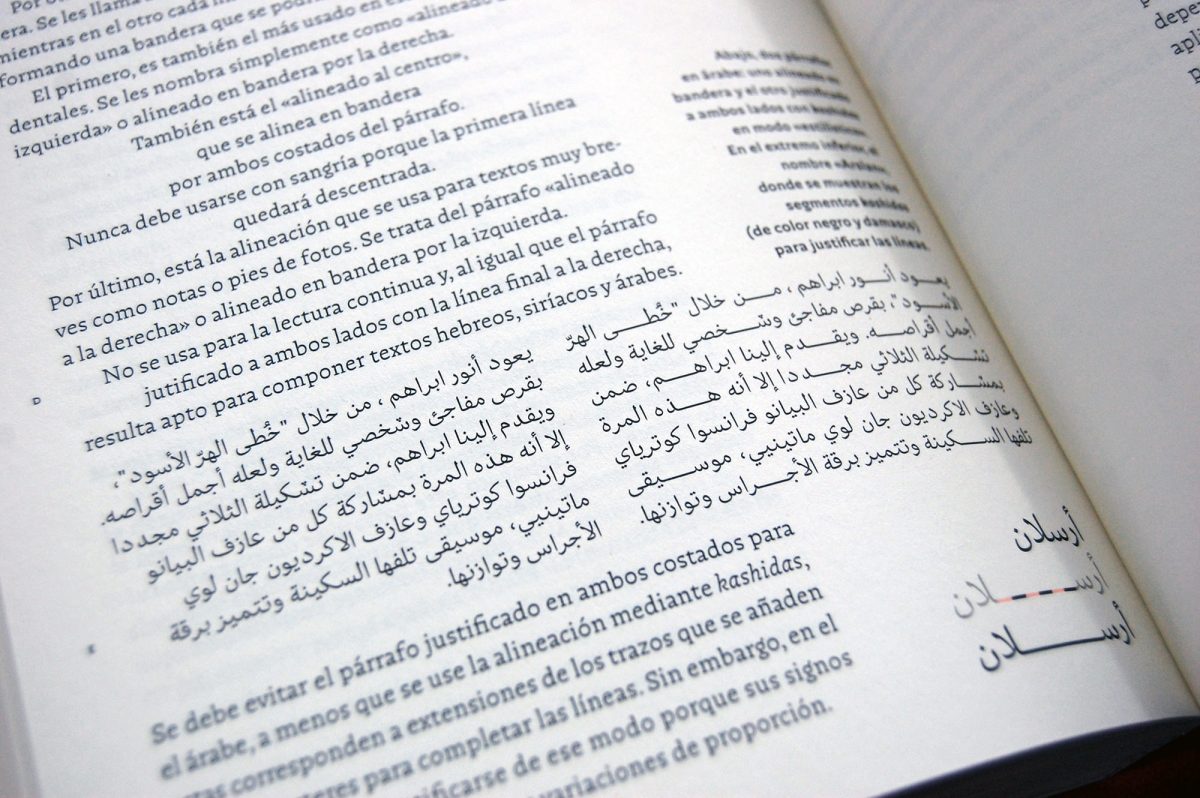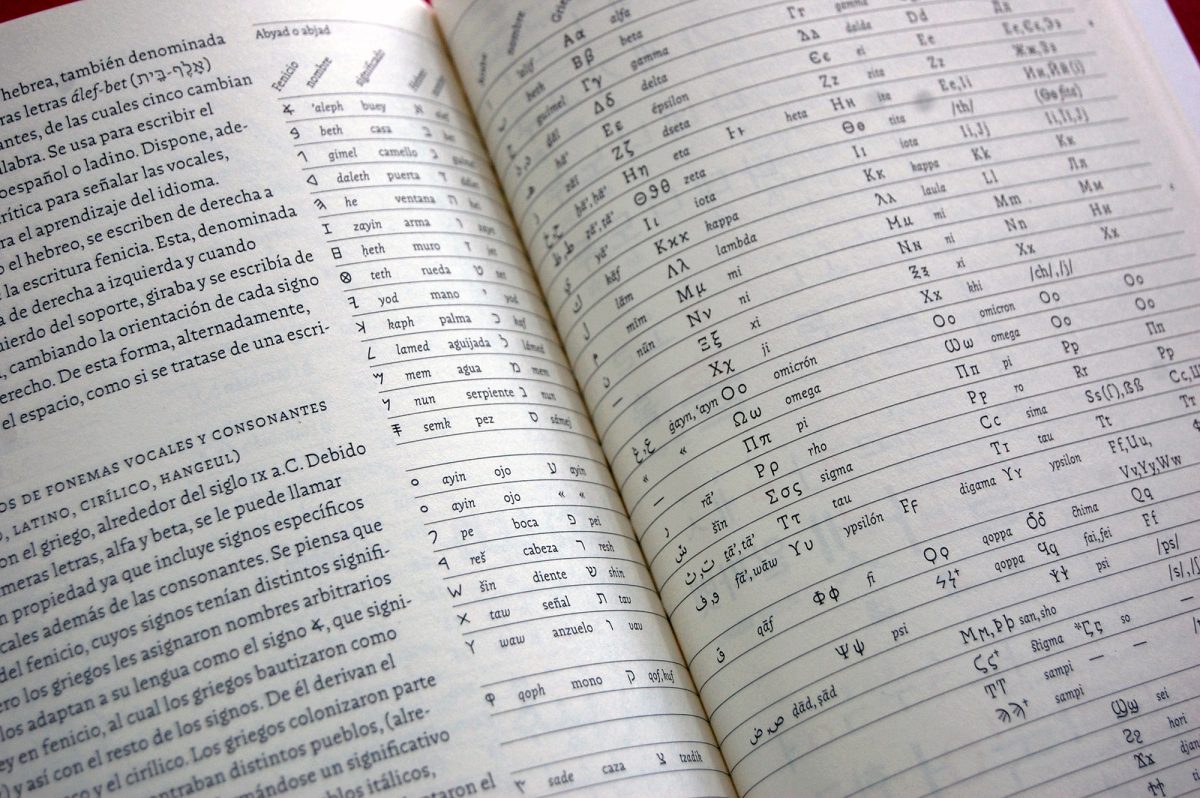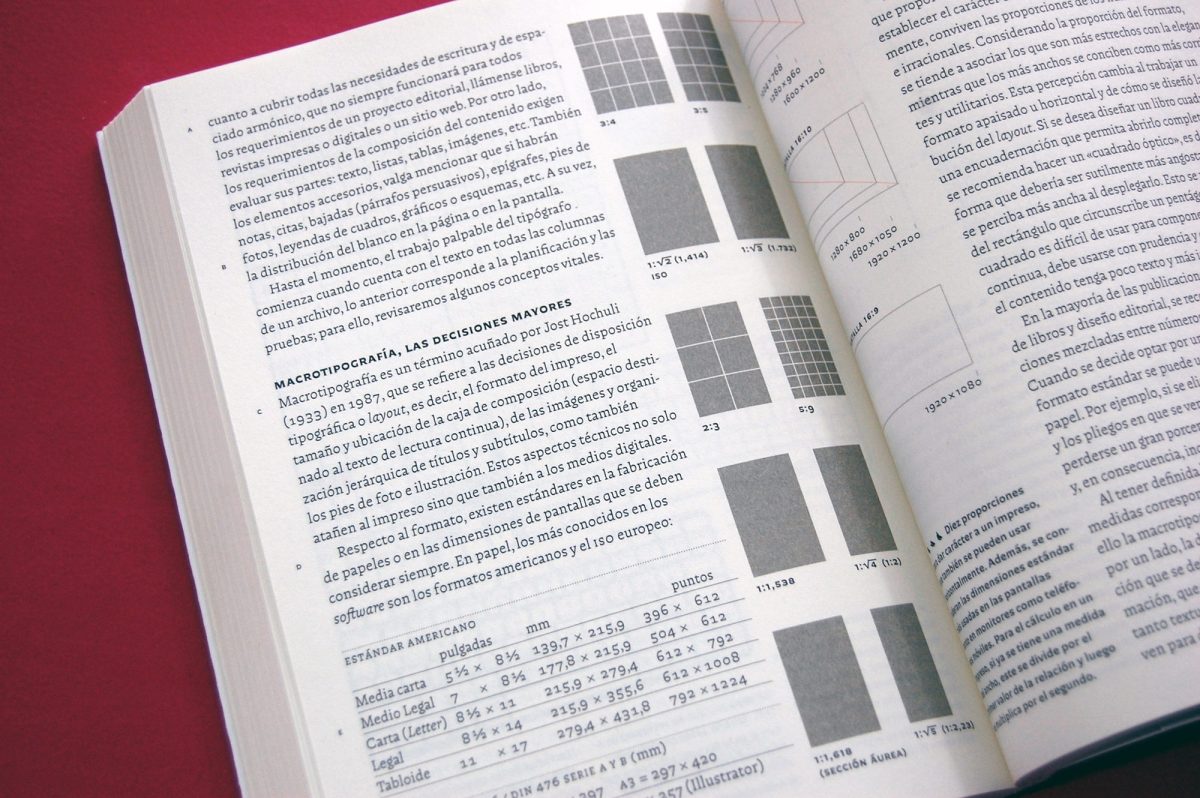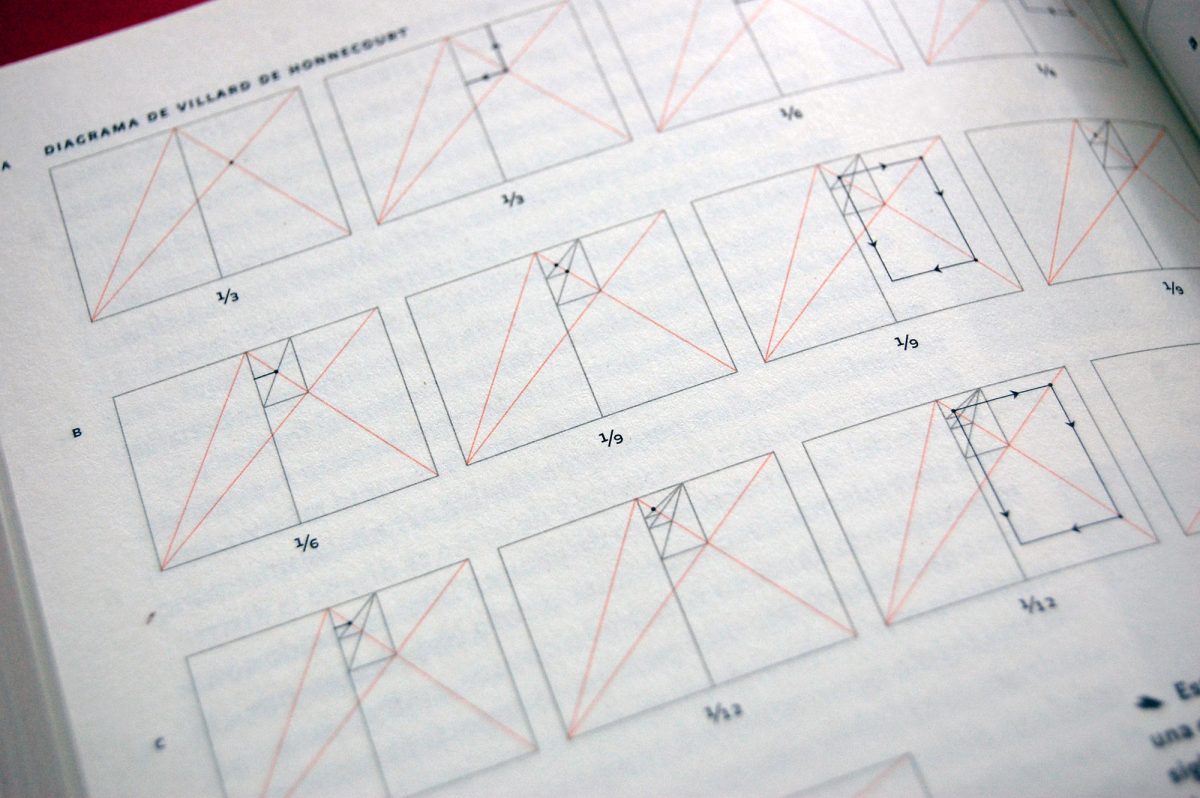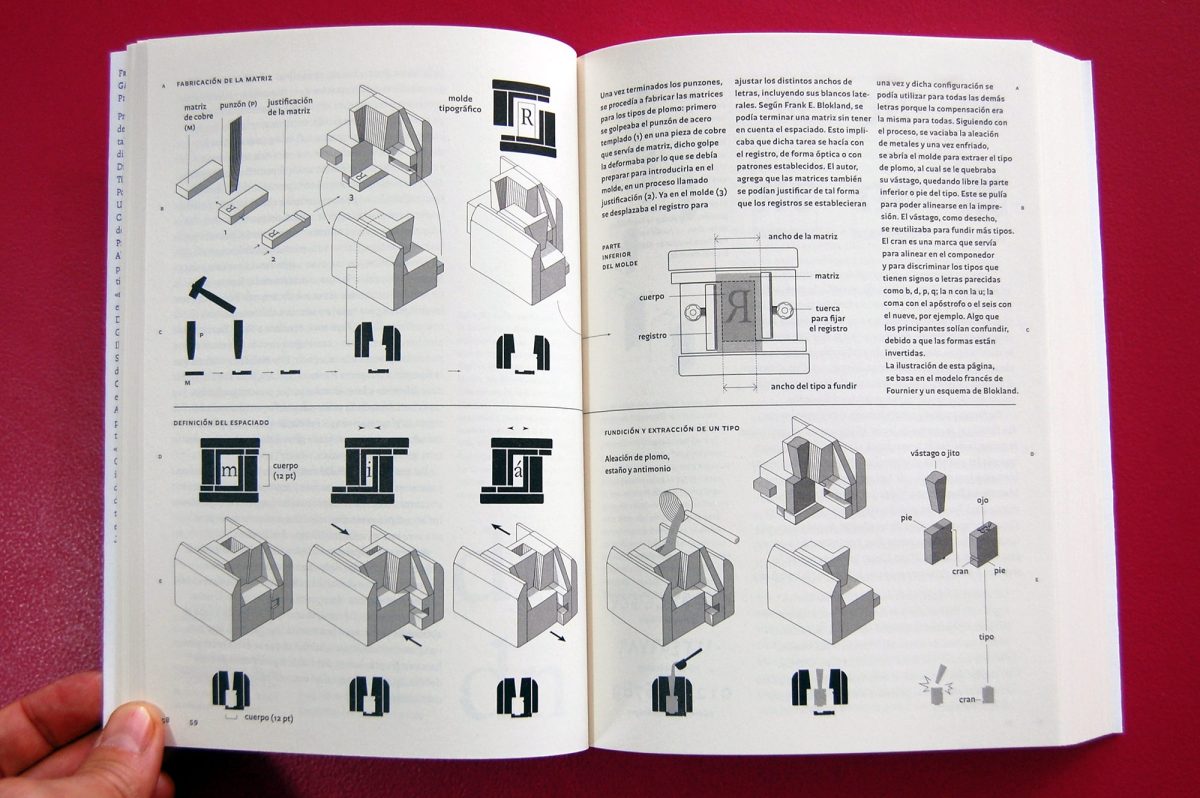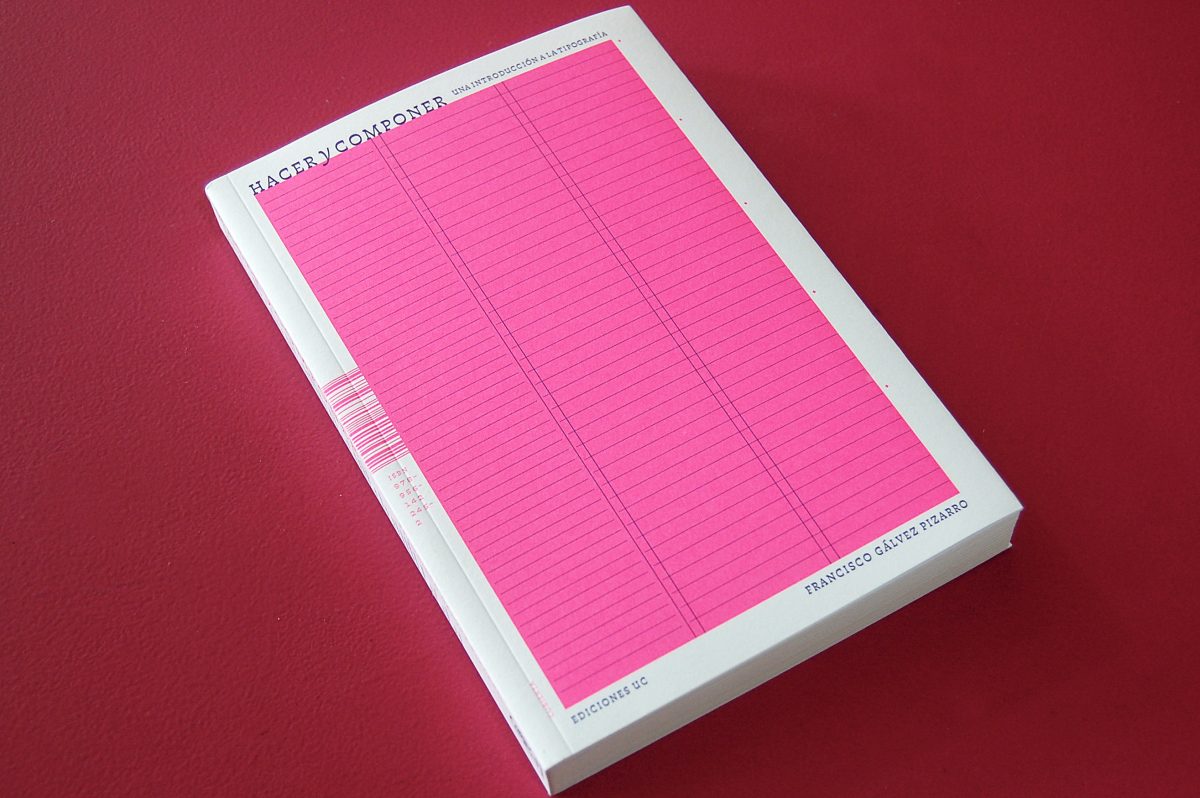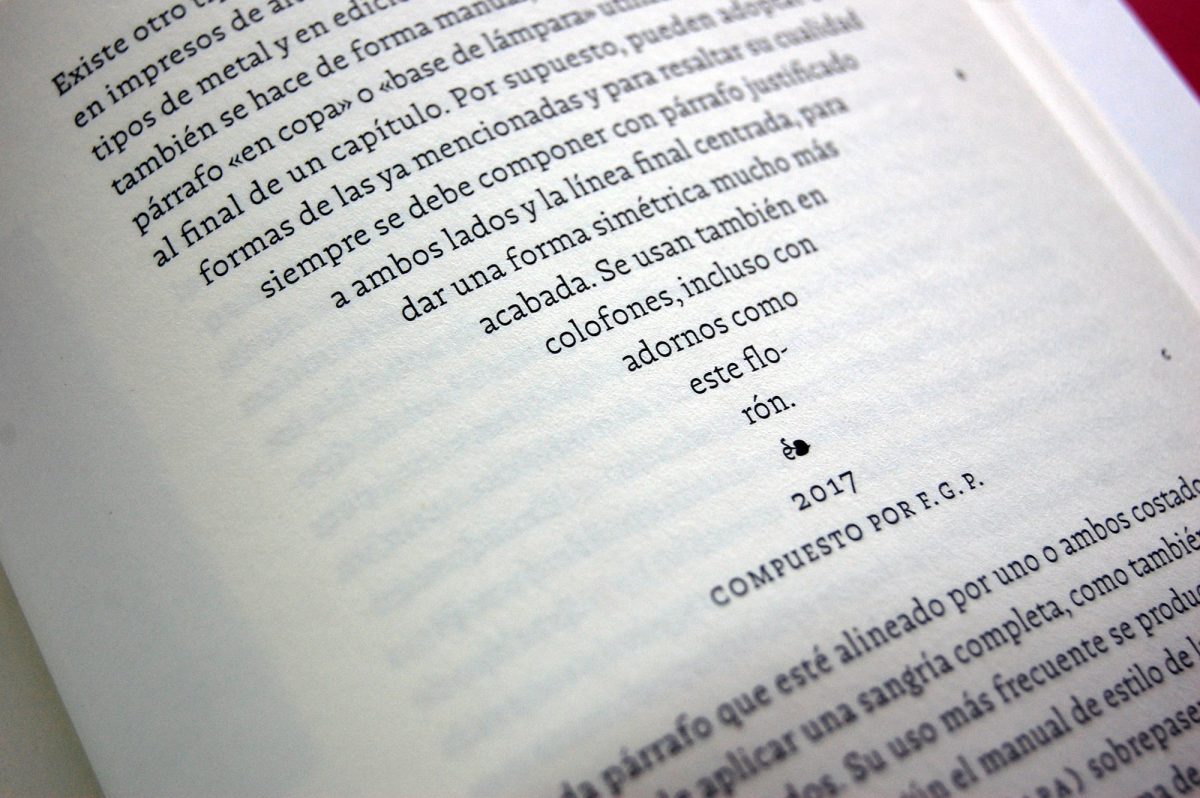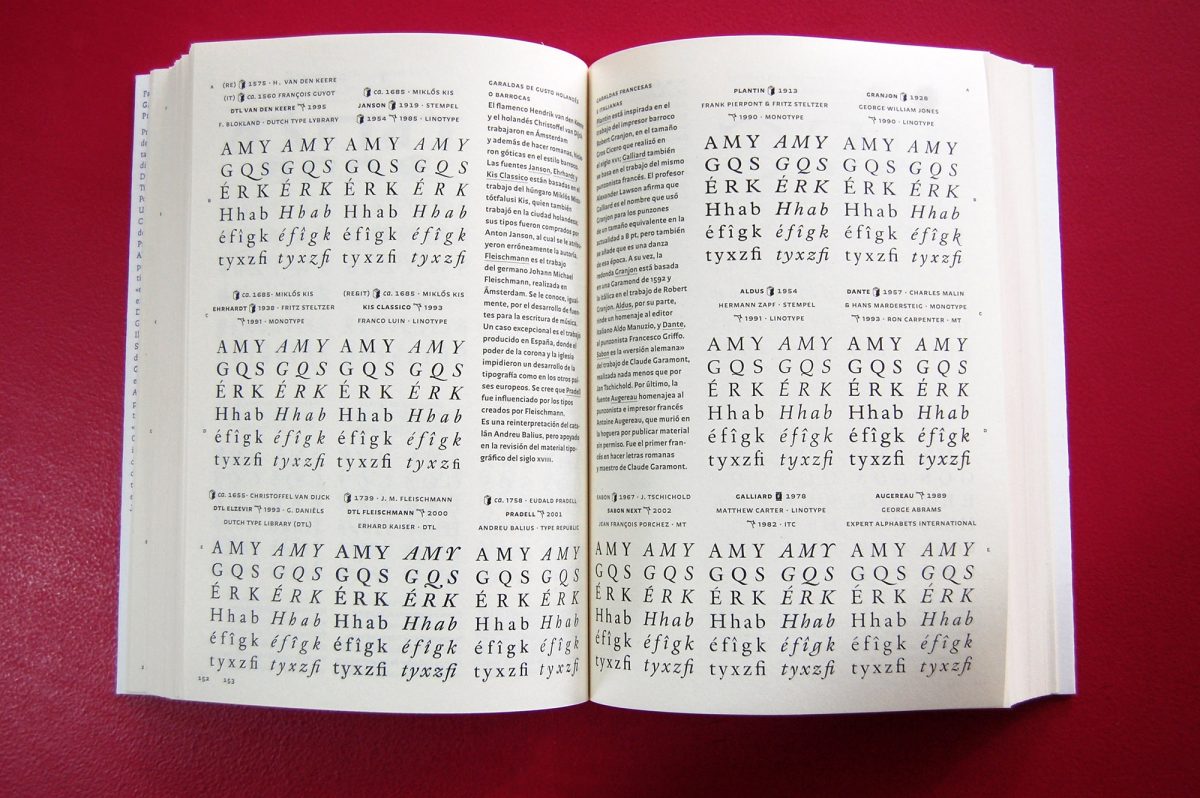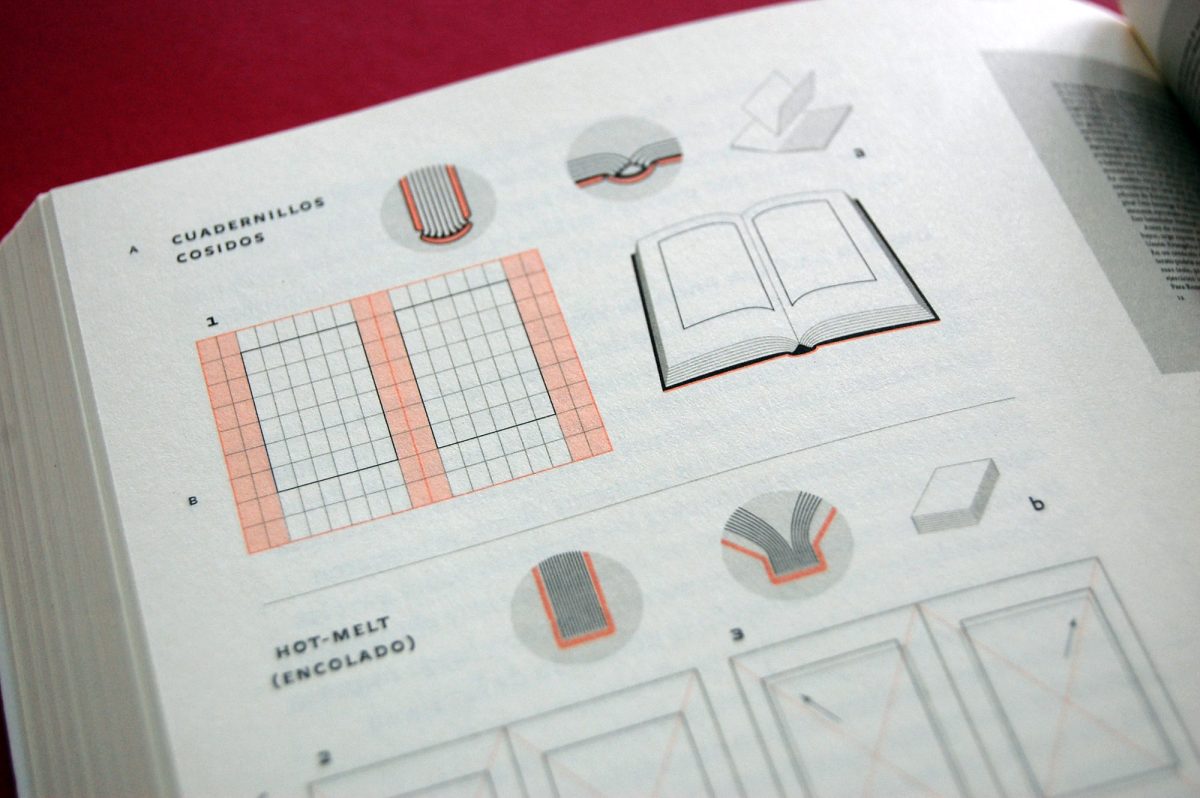
Pedagogía y generosidad
«Hacer y componer» de Francisco Gálvez (Editorial de la Universidad Católica de Chile) es, sin duda, un libro pedagógico. Como afirma Alejandro Lo Celso en el prólogo, se trata de un trabajo generoso, en el que se percibe la experiencia del autor en su actividad profesional. Como diseñador, tipógrafo, calígrafo y docente. Y, desde luego, esa generosidad se agradece.
Dos títulos de Campgràfic: “El ABC del lettering” de Iván Castro y el “Manual de tipografía digital” de Rodríguez Valero.
El planteamiento es ambicioso, sorprendente, y recuerda a la combinación de dos libros de Campgràfic, El abc del lettering 1 y el Manual de tipografía digital 2. Se aprecia una concepción integral de los aspectos que abarca la disciplina tipográfica, desde el saber y el hacer. Recorrer el libro es como estar en el aula: resulta muy didáctico, pues presenta un marcado carácter instrumental, apoyado constantemente con aportes históricos, teóricos y técnicos. Todo esto bajo la visión personal del autor, quien toma posición sobre la materia que describe, demostrando que estamos frente a un campo del conocimiento con bases sólidas pero en permanente construcción.
Esta toma de partido no solo se observa en temas puntuales, referidos a la letra o su uso, sino también en el recorrido y la organización de contenidos que propone. La estructuración comprende tres capítulos: la creación del signo tipográfico, el estudio del signo en sí mismo —que se define como parte de un sistema—y la puesta en página 3. Esta organización sugiere una lectura en cadena, donde unos temas van dando paso a los siguientes, en un in crescendo que culmina con la descripción de la labor del tipógrafo, una figura central para el autor, quien debe poseer una valiosa formación para ejercer su oficio responsablemente.
Esta visión está perfectamente resumida en el título del libro. Sin embargo, el subtítulo —«Una introducción a la tipografía»— sugiere una idea que, desde el punto de vista de la edición, permite plantear un disenso. El autor advierte en el prefacio que introducir a un tema implica, bajo el difícil procedimiento de la síntesis, proveer al lector de términos que no son de uso común para que estos sean comprendidos. Propone, en ese sentido, una introducción detallada. Esta propuesta hay que valorarla con relación a un elemento clave, el recorte: no en el sentido de qué incluir o qué no, sino de cómo se piensa la concatenación de temas. Una cuestión que conviene plantearse formulándose en primer lugar una pregunta que suele resultar muy efectiva para dilucidar este tipo de problemas: ¿quién es el lector de esta obra? Considero que, para este tipo de manuales, este interrogante resulta fundamental, y que la respuesta debe ser la construcción, desde la edición, de ese lector prototípico. Desde allí, el ordenamiento debería estar subordinado a ese lector, y no a la inversa, subordinando al lector al vasto conocimiento del autor.
Esclareciendo lo antedicho, considero que este manual puede resultar abrumador para un principiante, por una serie de procedimientos que más adelante se detallarán; no es una cuestión baladí el hecho de que en la amplia bibliografía, que recoge no pocos libros de Campgràfic, no aparezca referido el Manual de tipografía4. En cambio, para un especialista, puede ser entendido como una especie de manifiesto en el que se reordenan conceptos, la mayoría conocidos.
¿Por qué se dice que puede resultar abrumador para un principiante? Por el nivel de detalle con que se abordan los contenidos. Sin ser esto necesariamente un problema, sí lo es la manera en que dichos detalles aparecen, pues abundan ejemplificaciones o digresiones en el discurrir de un tema dado. En esa bifurcación del discurso se vierten conceptos, hasta entonces novedosos: cuestiones de estilos, «proporciones de tradición romana», de composición, kerning, tracking, etc. Aquí el lector deberá escoger su camino: inferir la relación análoga de esa cuestión novedosa con el tema principal, buscar más información al respecto, o saltearse directamente la referencia. Cualquier conducta que se de en la mente del lector —naturalmente imprevisible—, volver al hilo principal representará una tarea y esfuerzo adicional.
Esa falta de fluidez atenta contra la estructura progresiva planteada. Probablemente, la objeción aquí expresada se refiera a una cuestión de estilo, ya que ese «detallismo» también se observa en la navegación del libro. La construcción tipográfica de la pieza editorial es impecable y se evidencia la destreza del autor-diseñador en este terreno. Pero, por esa misma «deformación profesional» y ese gusto por el detalle, hay capas de información que confunden en lugar de aclarar. Concretamente, las referencias marginales, que son un sistema novedoso —o, al menos, poco visto—, muchas veces se «mezclan» o interactúan con las ilustraciones y con el texto, por esos juegos inconscientes de la percepción. Del mismo modo, los iconos o emojis utilizados añaden una capa de información a interpretar, en lugar de facilitar la lectura. Puede que, en relación con este planteamiento, debamos reivindicar aquí la figura del editor, otro profesional imprescindible en el desarrollo de cualquier publicación. O, mirando el asunto desde otra perspectiva, tal vez quepa presentar todo lo antedicho como un atributo favorable, a contracorriente de los tiempos que corren: al tratarse de una escritura pormenorizada, la lectura requiere tiempo.
Como ya se ha comentado, el libro se organiza en tres grandes capítulos, de manera secuencial. Además de ir encadenando los temas con profundo conocimiento, el autor hace relucir sus dotes como docente, ya que trabaja a menudo con la anticipación al fallo o a las construcciones teóricas erróneas. Dudo que puedan detectarse ese tipo de situaciones, con matices tan exactos, sin una trayectoria de años en la enseñanza.
Tipos de plomo de la Súper Veloz de Joan Trochut. Fotografía provista por J. L. Martín Montesinos.
En el primer capítulo, la creación de letras, nos encontramos con el privilegio de encarar temas cruciales —caligrafía, rotulación y diseño de tipos— a través del oficio del autor, y de lo que ese hacer enseña. Encuentro detalles dignos de mención, como la aclaración sobre la caligrafía china o sobre la herramienta de la pluma de punta recortada, la explicación de las formas y contraformas como blanco y negro desnudo, la valoración del ritmo en su dimensión gráfica o la defensa de la importancia de la caligrafía, cuestión esta última sobre la que también Ivan Castro trata para explicar la rotulación, porque conocer y practicar caligrafía es fundamental para conocer la estructura de las letras, el espacio, el ancho. Se agradecen las referencias a Rudolf Koch y a la Super Veloz de Joan Trochut, tipografía modular que personalmente pude utilizar en plomo cuando era un joven tipógrafo, digitalizada en 2004 en un buen trabajo-homenaje de Andreu Balius y Alex Trochut.
Portada del libro “El trazo” de Gerrit Noordzij, editado por Campgràfic, Valencia.
La experiencia se torna más próxima, ya que ese saber se transmite en nuestro propio idioma, y desde la perspectiva que se construye diseñando y aprendiendo, siempre con muy buenos ejemplos personalizados para el libro. Hay riqueza en el desarrollo de los temas, desde el trabajo con los materiales y las técnicas, el anclaje con referencias históricas y la inclusión de teorías específicamente tipográficas como la de El trazo de Gerrit Noordzij 5.
3. Siguiendo la noción de signo triádico de Peirce: las preconfiguraciones, su existencia en sí y su actualización. ↩
4. Martín Montesinos, J. L., Mas Hurtuna, M. (2016). Manual de tipografía. Del plomo a la era digital. València: Campgràfic. ↩
5. Noordzij, G. (2009). El trazo. Teoría de la escritura. València: Campgràfic, sobre el cual pude escribir una reseña en la revista Tipográfica, recientemente digitalizada. ↩